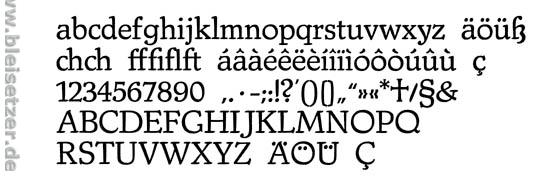
geben wird es diese schrift ja sicherlich, also ist das eine aufgabe
für 'den dicken mit dem blei'. ggf. findest du ein paar schriftmuster.
die frage ist nur, ob das dein kunde schätzt – du könntest ihm sicher-
lich auch eine andere/schönere vorschlagen, er wird den unterschied
wohl kaum sehen, wenn er diese schriftart mit »times oder so« betitelt.
IDEALerweise habe ich BLAUE AUGEN (von wegen kein gefühl...)
pps: apropos weiß (wie der polar): Weiß Antiqua
1. Vorsitzender am Bundesgeschmacksgericht, oder was?
Mal im Ernst, es waren Vorschläge auf die Schnelle, keine Diplomarbeit.
mir gefällt gerade die fairplex. und das obwohl ich eigentlich
nur die condensed version davon mag. klar es ist was komplett
anderes, aber es sieht gut aus. sorry. 8)
die geschmäcker sind verschieden.
Ich denke, Ralf wäre sehr wohl in der Lage, die 7 Buchstaben für das Logo nach dem Original ohne Mühe hinzulegen. Aber er hat trotzdem um ein Brainstorming gebeten. Und das gibt's gerne, gerne auch in alle mögliche Richtungen. Darum ja auch "Forum" und nicht "Contest". Darum ist auch die Celeste ein guter Vorschlag.
Und um noch eins draufzusetzen: Fairplex wide bold
und warum seid ihr so gereizt wenn jemand nicht die gleiche meinung teilt?
ist das dann ein forum? ich habe keine vorschläge gemacht, weil mir keine passenden bekannt sind.
Über ausführlich begründete Urteile regen wir uns dann später auf ...
Der Kunde wünscht sich für die Neubelebung dieser Firma aus den 40ern eine »Times oder so«. :evil:
Was käme dem Original (das Ventimotor) näher? Whatthefont ignoriert leider die charakteristischen Serifen.
mal davon ausgehend, daß Du ja nicht zwingend diese Schrift klassifizieren mußt, sondern eine finden willst, die dieser ähnelt:
Liberta-Antiqua mager
TypoArt, Dresden
Erstguß 1958
Herbert Thannhaeuser
Ich meine, Andreas Seidel hätte mir mal gesagt, daß es die auch digitalisiert gibt.
Die Schrift im Muster ist um mindestens 25 Jahre älter.
So.. ich muß wieder.
Es nimmt kein Ende.
und warum seid ihr so gereizt wenn jemand nicht die gleiche meinung teilt?
ist das dann ein forum? ich habe keine vorschläge gemacht, weil mir keine passenden bekannt sind.
Ich hab jetzt ein ganzes Wochenende gebraucht, um mich da jetzn einzumischen, aber als ich das da wieder gelesen habe ist ma schon wieder des Gimpfti aufgangen. Das passt von vorn bis hinten net, bitteschön. Einer anderen Meinung sein und jemand anderen gefühllos nennen sind also schon zwei Paar Schuhe. Wie der liebe Georg an anderer Stelle schon gemeint hat "ich mag es nicht wenn ich (oder andere) vorgeführt werden." (So oder ähnlich, sinngemäß)
Der Sinn eines Forums mit Qualitätsanspruch wie es dieses ist, sollte sich nicht darin bescheiden mit Statements wie
"what the font ist schlau hat aber kein gefühl"
"also hast du kein gefühl"
"mal im ernst, deine vorschläge vor allem die fairplex gehen gar nicht."
wenn man vorher nicht einmal
a) eigene vorschläge geliefert hat oder
b) sein eigenes Missfallen ordentlich begründet
Das hat NICHTS mit anderer Meinung haben zu tun, das ist ungenügender Gesprächsstil und mangelnder Respekt dem anderen gegenüber.